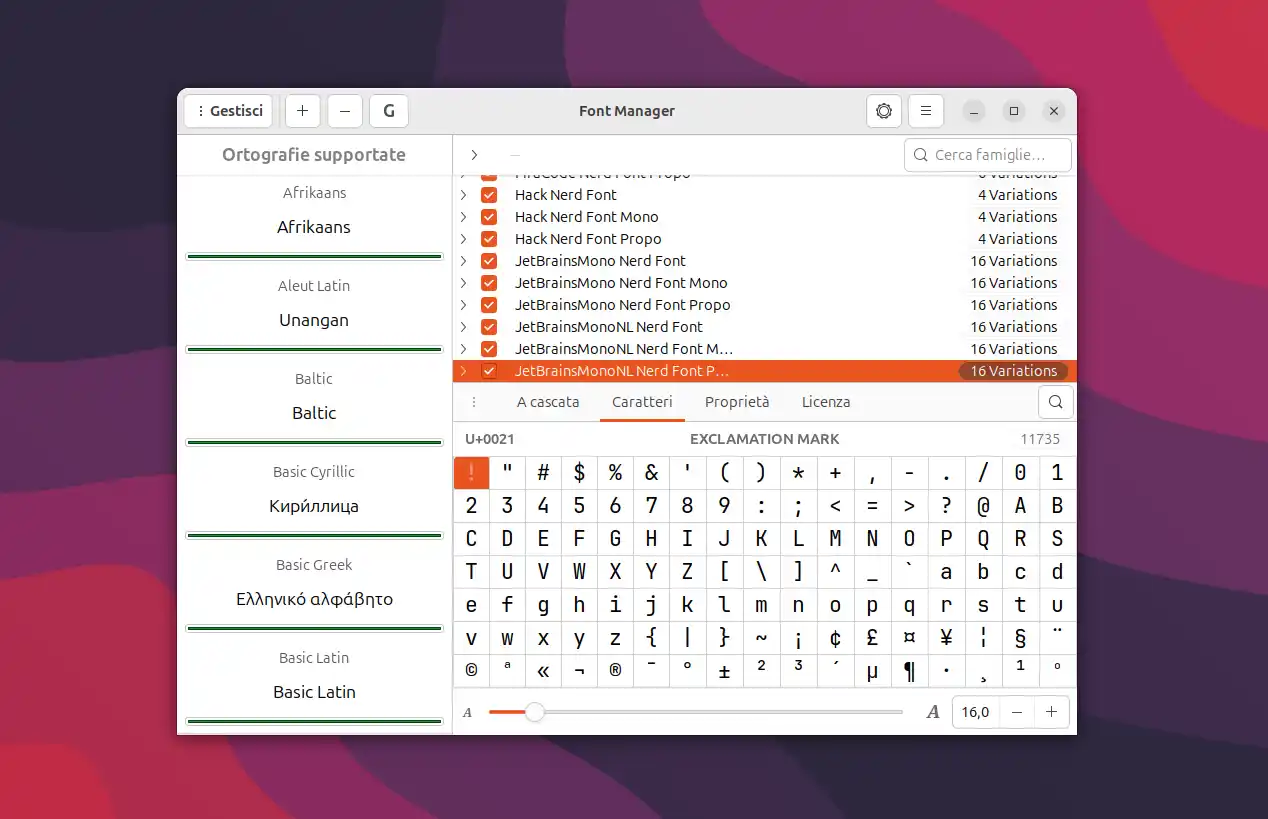
Nefoin installare i Nerd Fonts su Linux e macOS
I Nerd Fonts sono font modificati che includono icone e glifi utili per sviluppatori, amministratori di sistema e appassionati di personalizzazione. Sono ampiamente utilizzati in terminali, editor di codice (come VS Code o Vim) e strumenti come Tmux o Polybar per migliorare l’estetica e la leggibilità. Tuttavia, installarli manualmente richiede tempo: bisogna scaricarli uno per uno, estrarli e copiarli nelle cartelle di sistema.
Nefoin risolve questo problema automatizzando l’intero processo. Questo script shell open source semplifica l’installazione, l’aggiornamento e la gestione dei Nerd Fonts su Linux e macOS con pochi comandi.
Cos’è Nefoin?
Nefoin sta per “Nerd Font Installer”. È uno script da riga di comando leggero che recupera e installa i Nerd Fonts direttamente dalla release ufficiale su GitHub. Che tu sia su Linux o macOS, funziona allo stesso modo.
È pensato per chi desidera:
• Installazioni rapide,
• Meno ingombro,
• Nessun passaggio manuale.
Nefoin non include font né ti obbliga a installare componenti aggiuntivi. Scegli il font. Nefoin fa il resto.
Perché Usare i Nerd Fonts?
Potresti chiederti perché dovresti voler usare i Nerd Fonts.
I Nerd Fonts sono versioni speciali di font popolari come FiraCode, Hack o JetBrainsMono. Sono arricchiti con:
• Icone extra (per alberi di file, terminali e linee di stato),
• Simboli utili per sviluppatori (come per powerlines e vim),
• Spaziatura coerente in terminali e editor di codice.
Se utilizzi Neovim, tmux o qualsiasi window manager a tiling, i Nerd Fonts sono quasi essenziali.
Caratteristiche di Nefoin
Potresti chiederti: e riguardo a getnf o ai download manuali? Ho provato il metodo manuale. Non è così difficile. Tuttavia, trovo che usare Nefoin sia molto più semplice.
Nefoin è Più Veloce
Altri strumenti clonano l’intero repository dei Nerd Fonts. Sono oltre 2GB. Nefoin scarica solo il font desiderato dalla pagina delle release su GitHub. È leggero e rapido.
Nefoin è Più Semplice
Nessuna interfaccia grafica, nessuna configurazione e nessun pacchetto da installare. Passi il nome del font come variabile, e fa tutto il resto.
Nefoin Funziona Bene negli Script
È un piccolo script shell (~100 righe). Ciò lo rende facile da automatizzare nei dotfiles o da usare nei container Docker.
Elenco di Nerd Fonts Popolari che Puoi Installare
Nefoin supporta qualsiasi font elencato nelle release di ryanoasis/nerd-fonts che termina con .zip.
Alcuni font Nerd comuni sono:
• Hack
• FiraCode
• JetBrainsMono
• Iosevka
• Meslo
• CascadiaCode
• UbuntuMono
• SourceCodePro
• RobotoMono
Basta sostituire il nome nel comando, e sei a posto.
Installare i Nerd Fonts con Nefoin in 4 Passaggi
Ti mostrerò come ho installato un font usando Nefoin in soli 4 passaggi sul mio sistema Ubuntu 24.04 LTS. Userò FiraCode Nerd Font come esempio.
• Su Linux: ~/.local/share/fonts
• Su macOS: ~/Library/Fonts
Se il font esiste già, chiederà prima di sostituirlo.
Passaggio 3: Aggiornare la Cache dei Font
Su Linux:
Su macOS, la cache viene aggiornata automaticamente.
Passaggio 4: Verificare i Nerd Fonts
Puoi verificare se il font è installato correttamente aprendo un terminale e controllando se il font appare nell’elenco dei font disponibili. In alternativa, puoi utilizzare un’applicazione che supporta i Nerd Fonts per vedere se le icone e i simboli vengono visualizzati correttamente.
Prova i Nerd Fonts in un Container Docker
Se desideri testare i Nerd Fonts in un ambiente isolato, puoi utilizzare un container Docker. Ecco un esempio di come farlo:
All’interno del container, puoi seguire gli stessi passaggi sopra descritti per installare e verificare i Nerd Fonts.
Suggerimento Bonus: Installare Font Personalizzati
Conclusione
Nefoin è uno strumento semplice e veloce per installare i Nerd Fonts su Linux e macOS. Con un solo comando, puoi avere il tuo font preferito pronto all’uso, senza complicazioni.